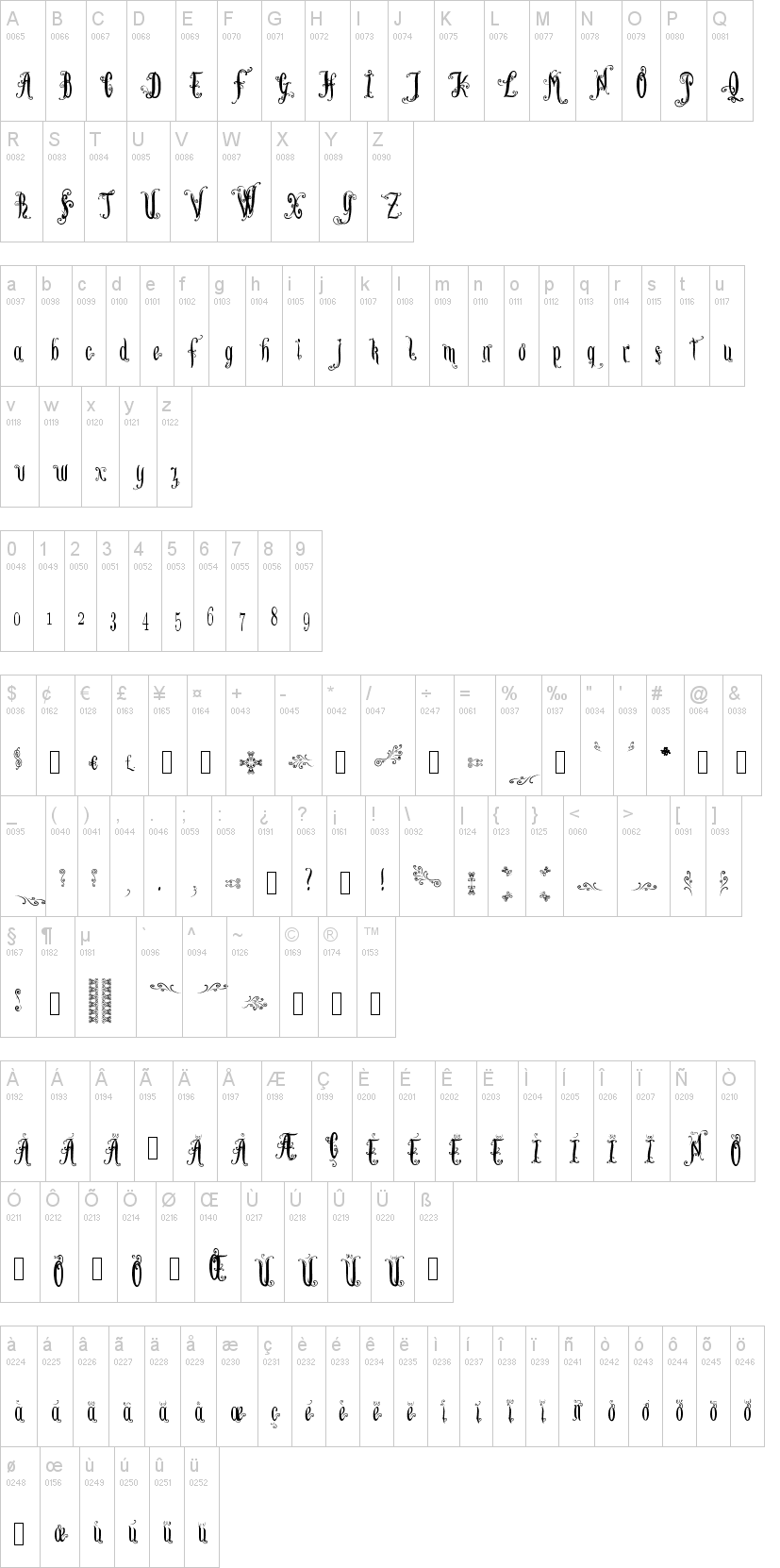
Lutin Paniquangoisse 是一款设计师 Louis-Rémi Babé 创作的一款粗体字体。这款字体被设计成一种极具表现力的、充满活力的字体,它的字体特点是大胆、醒目、古典、现代、复古、时尚,可以满足不同类型的设计需求。Lutin Paniquangoisse 字体的字形非常细腻,字体的笔画细致,给人以灵动的感觉。它的字形拥有更多的变化,可以满足不同的设计需求,可以增加字体的表现力和视觉效果。内容介绍
Lutin Paniquangoisse是一款非常不错的手写艺术字体,具有很好的视觉感,适合于文化类的宣传设计、商业类品牌的广告和产品包装设计以及个性化文字排版等较多场景。